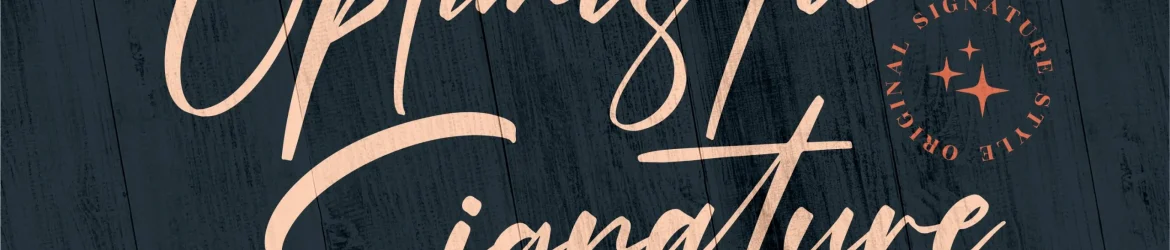
Optimistic Signature Font – Download Grátis
A Optimistic Signature Font é uma elegante opção para designers que procuram um estilo moderno para suas criações, a serviço de uma ampla gama de projetos. Feito pela Perspectype Studio, essa fonte premium é perfeita para o lançamento de logomarcas e embutir um toque personalizado em qualquer projeto de branding. Sujeitos a designs de mobília, embalagens de produtos, tigelas, cartões-postais com citações, outdoors, sacolas de viagem, camisetas, capas de livros, cards de nomeação, convites e etiquetas, esta fonte é uma escolha perfeita para aqueles que valorizam um toque único e sofisticado em seus trabalhos. Seja em festivais especiais ou no desenvolvimento de produtos de luxo, a Optimistic Signature Font entrega o sabor premium desejado de maneira natural e elegante.